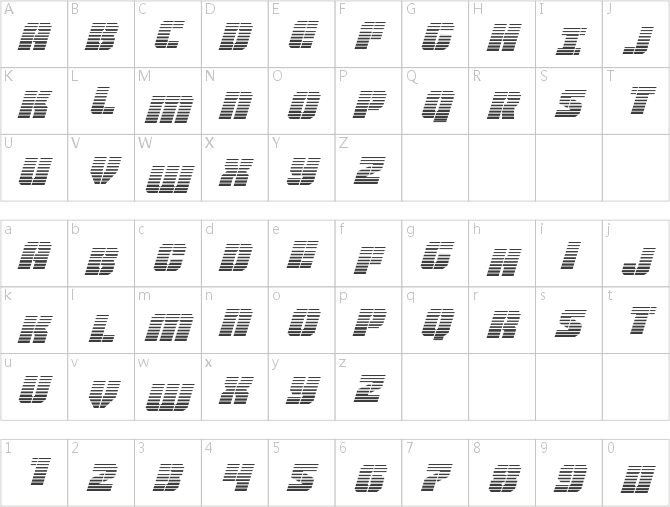
Warp Thruster Gradient Italic
Warp Thruster Gradient Italic介绍
Warp Thruster Gradient Italic字体字库是一款让人赏心悦目、百看不厌的英文字体,适合各类广告和产品包装设计应用,字体大小0.06MB,格式为ttf字体,上传用户是凡客,作者/版权方为未知